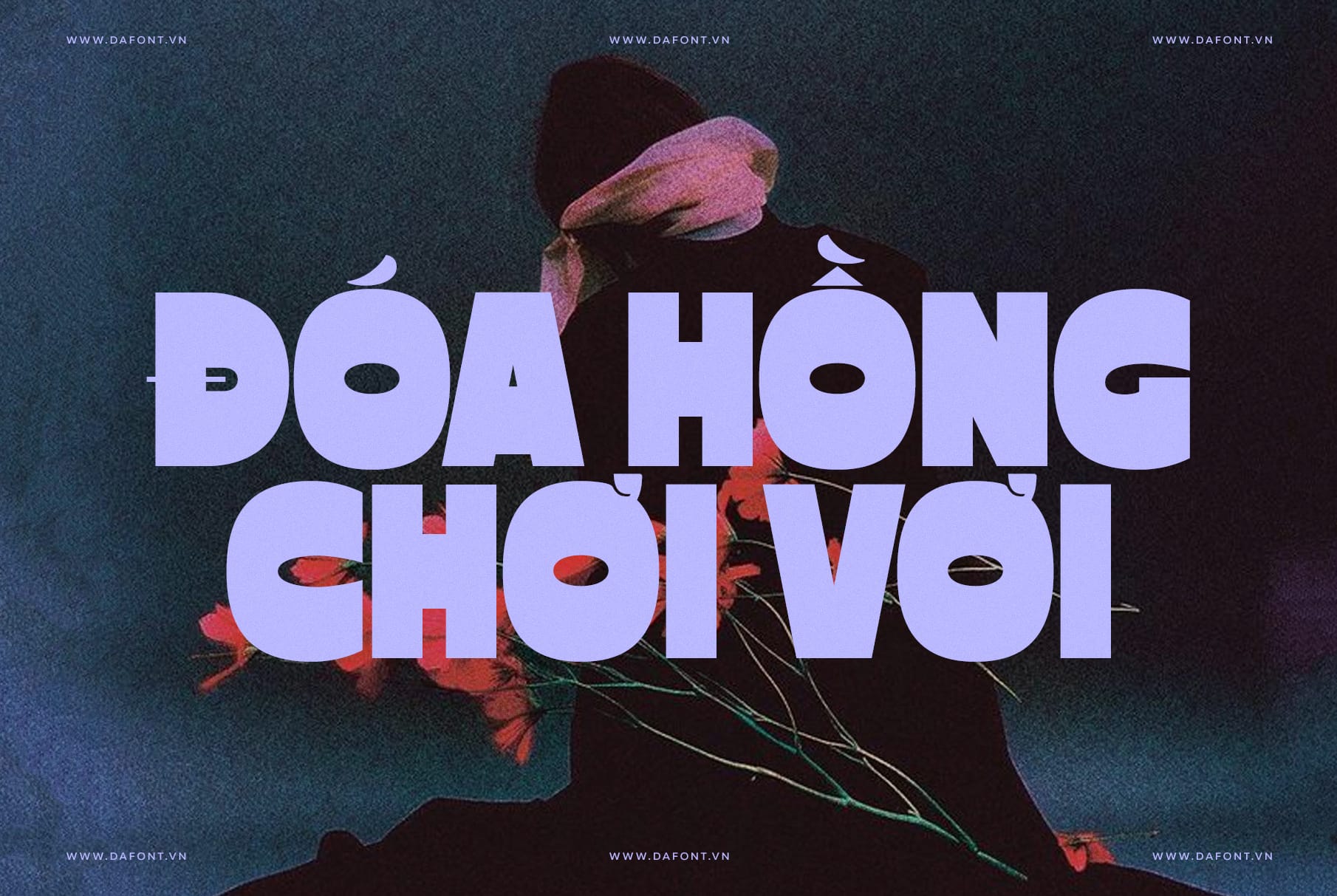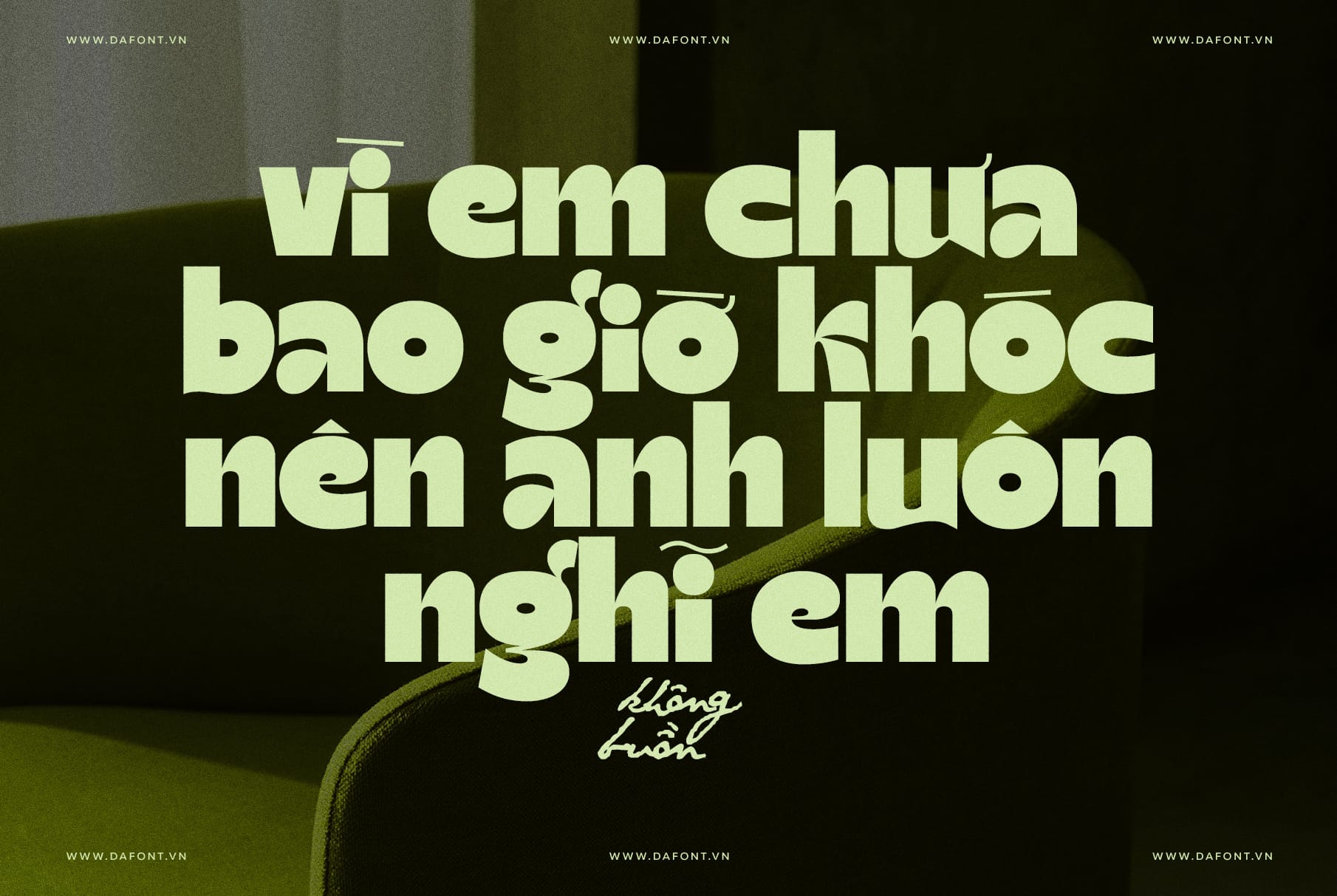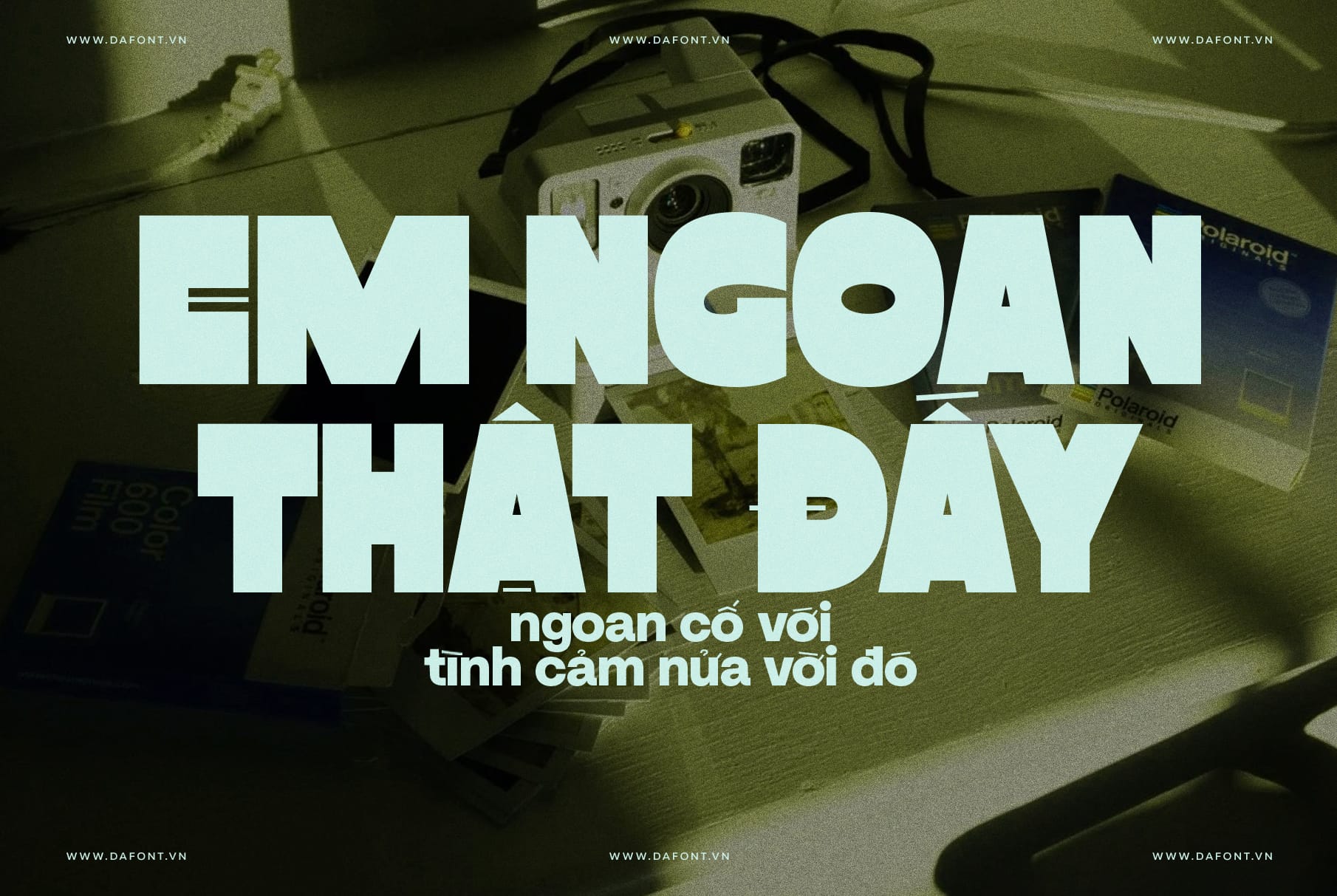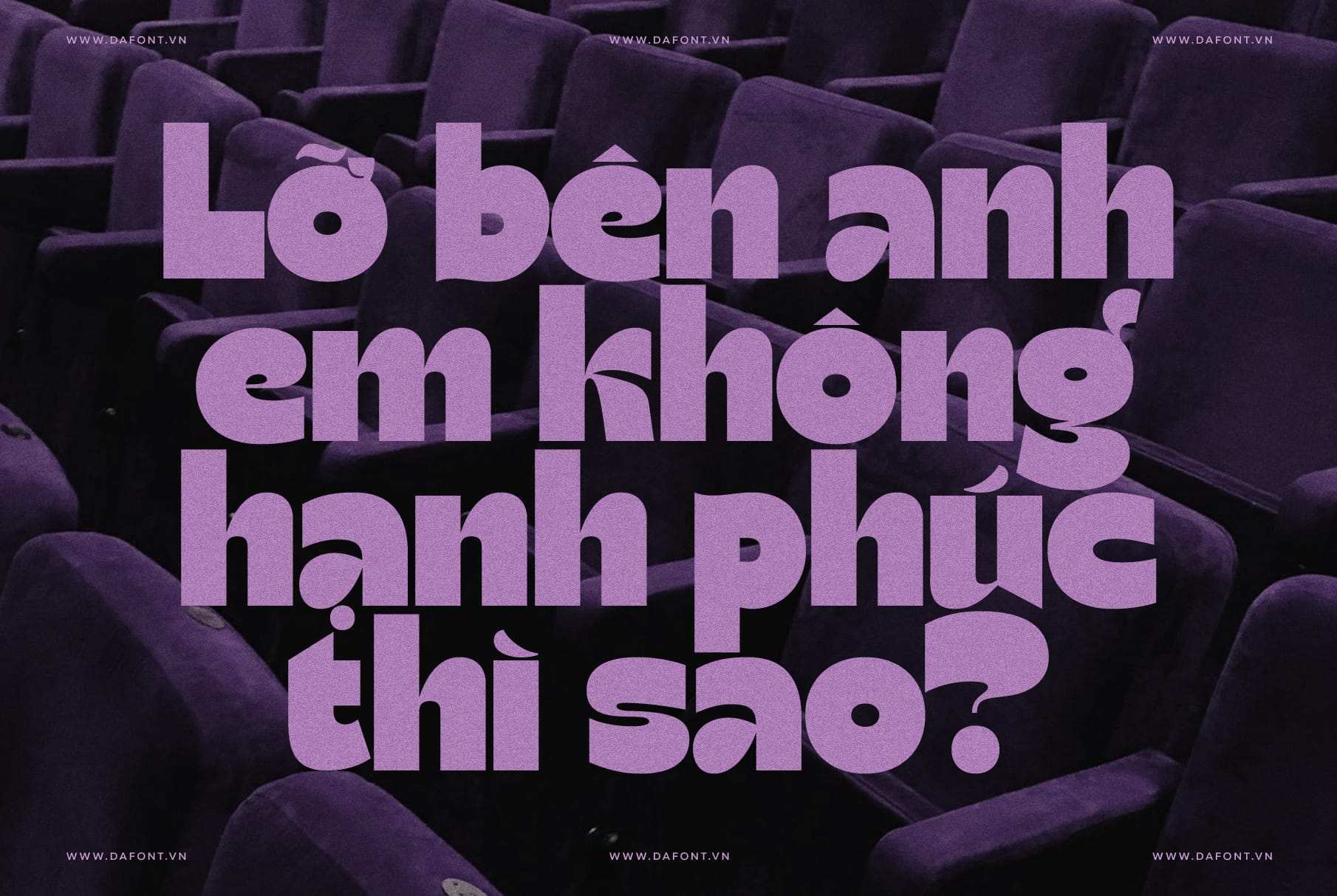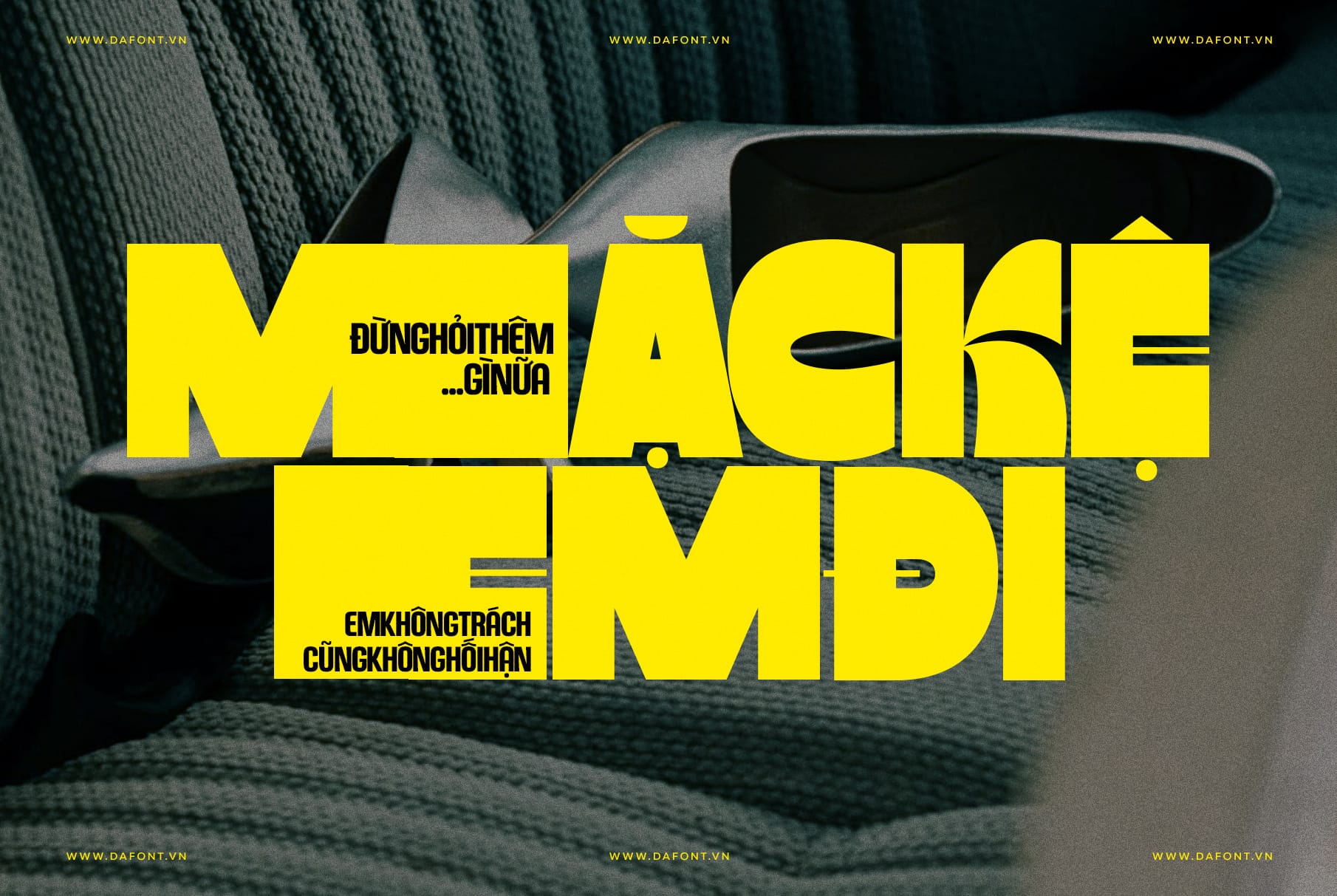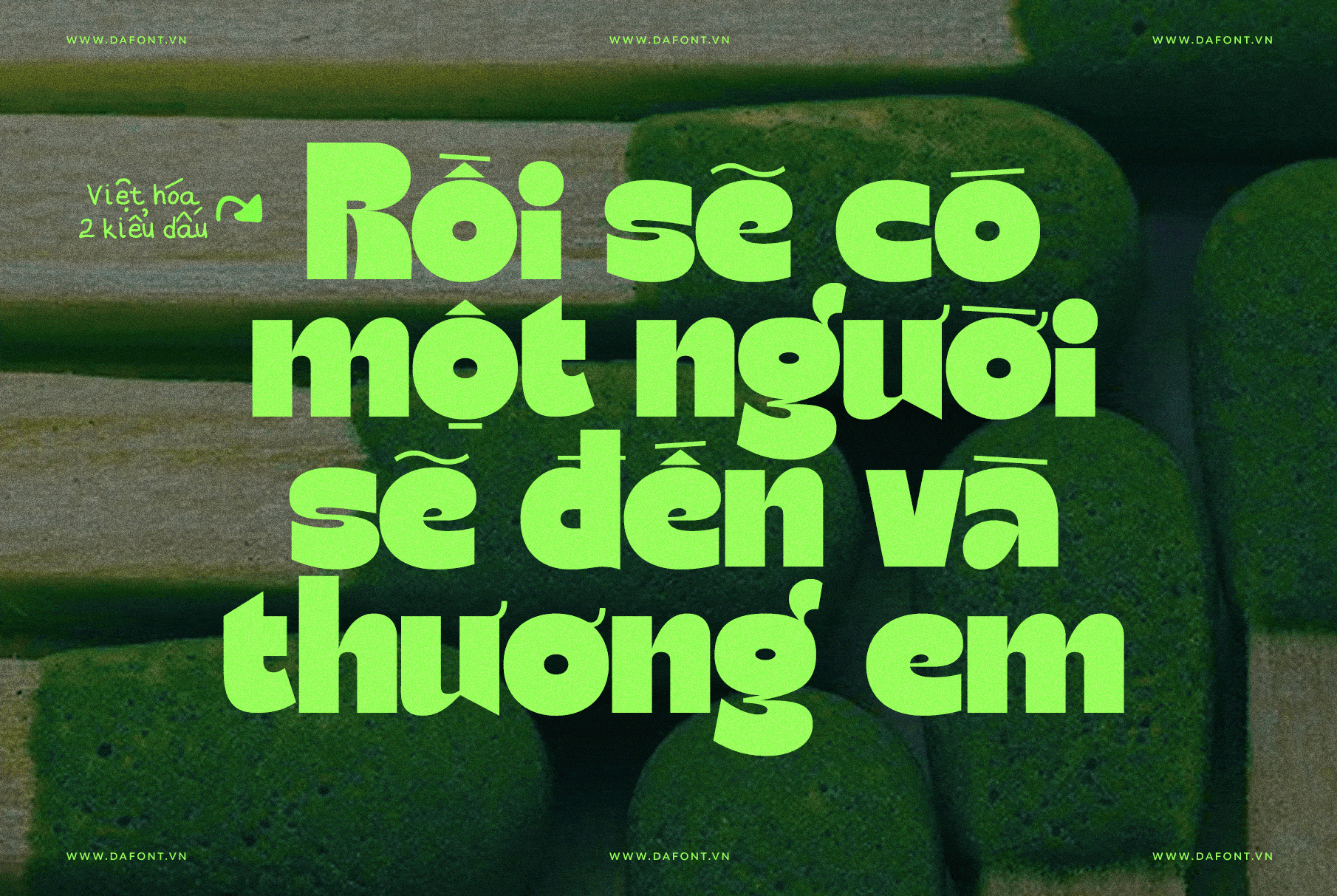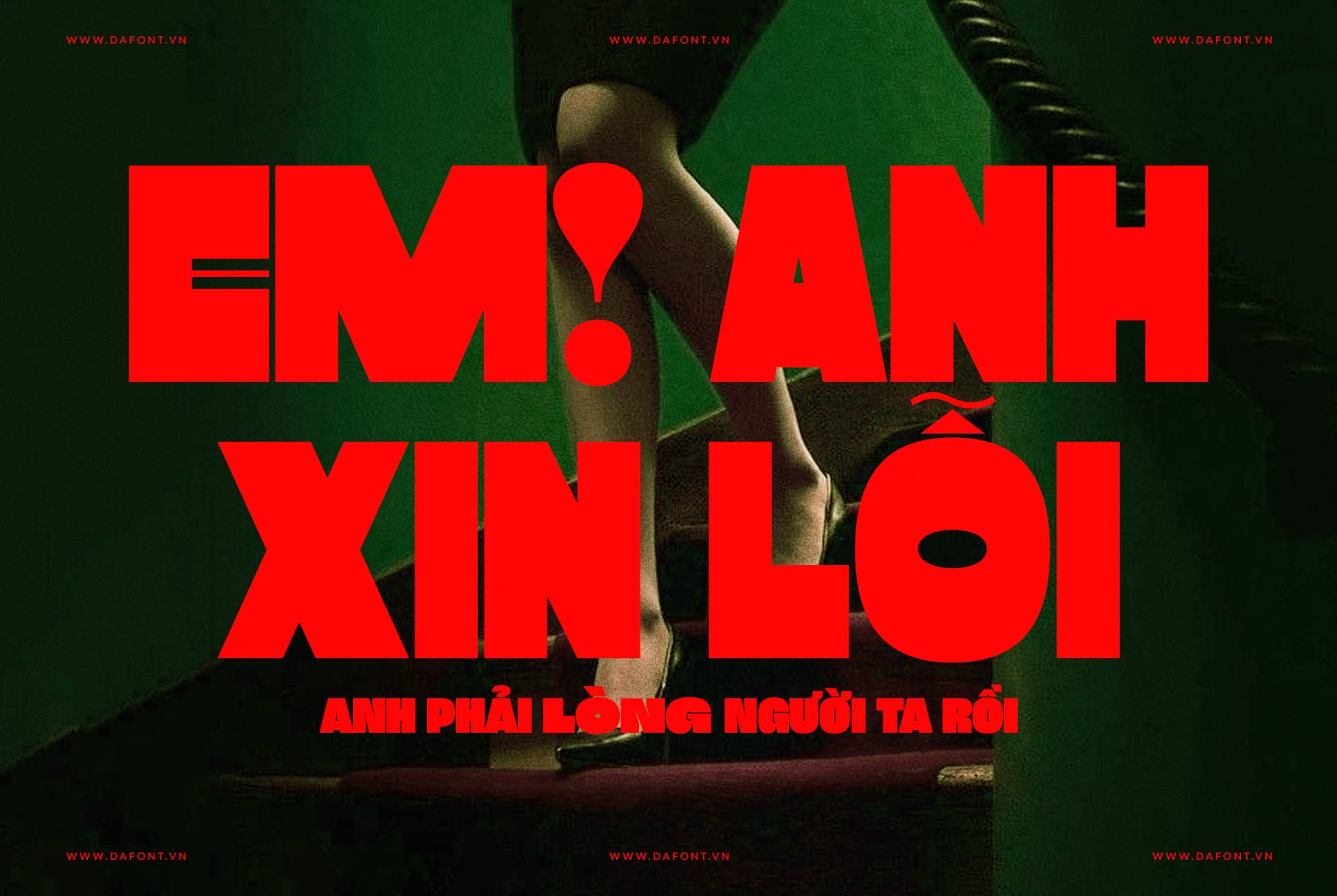
DFVN TAN – FLOWER MARKET là một kiểu chữ display được thiết kế với tinh thần mạnh mẽ, cổ điển nhưng vẫn phóng khoáng và hiện đại. Mỗi ký tự trong font như một bông hoa nở rộ giữa khu chợ đầy sắc màu – vừa có cấu trúc vững chắc, vừa có nhịp điệu tươi vui và giàu cảm xúc.
Với các đường nét dày, các đường cong bo tròn tinh tế và những chi tiết “quirky” đặc trưng, DFVN TAN – FLOWER MARKET thể hiện sự cân bằng hoàn hảo giữa vẻ retro hoài niệm và tinh thần sáng tạo đương đại. Đây là kiểu chữ sinh ra để thu hút ánh nhìn, tạo điểm nhấn mạnh mẽ cho các dự án cần cá tính thị giác – từ logo thương hiệu, poster nghệ thuật, bao bì sản phẩm, cho tới bài đăng mạng xã hội.
Không chỉ dừng lại ở vẻ đẹp hình khối, font còn thể hiện sự tinh tế qua cấu trúc hình học chắc chắn và độ tương phản rõ nét, giúp thiết kế của bạn trở nên nổi bật, tự tin và tràn đầy năng lượng.
Đặc điểm nổi bật DFVN TAN - FLOWER MARKET
Các đặc điểm nổi bật của TAN - FLOWER MARKET tập trung vào khả năng gây ấn tượng mạnh ở cỡ lớn, chất hiện đại–retro vui tươi, và sự linh hoạt trong ứng dụng thương hiệu, in ấn và mạng xã hội.
Nét chữ đậm, mạnh mẽ và chắc chắn
DFVN TAN - FLOWER MARKET mang phong cách display bold với thân chữ to, dày và cân đối. Mỗi ký tự như một khối hình học được gọt giũa kỹ lưỡng, mang lại cảm giác vững chãi, sang trọng và đầy tự tin. Khi dùng ở kích thước lớn, font tạo hiệu ứng thị giác mạnh, giúp tiêu đề hoặc logo nổi bật ngay từ cái nhìn đầu tiên.
Cảm hứng retro pha hiện đại
Lấy cảm hứng từ typography cổ điển của thập niên 70–80, TAN – FLOWER MARKET mang đến không khí hoài niệm nhưng vẫn phảng phất nét đương đại và tinh tế. Các đường cong bo tròn, phần đầu chữ mềm mại cùng tỉ lệ hiện đại giúp font dễ ứng dụng trong nhiều xu hướng thiết kế hiện nay — từ vintage poster, branding, đến editorial art direction.
Việt hóa với 2 kiểu dấu tinh chỉnh riêng biệt
Phiên bản DFVN Việt Hóa được hoàn thiện với hai bộ dấu tiếng Việt khác nhau:
• Kiểu dấu mặc định: Cân đối, rõ nét, phù hợp cho thiết kế thương hiệu, tiêu đề hoặc nội dung cần sự chuyên nghiệp.
• Kiểu dấu mảnh mang phong cách retro: Nhẹ nhàng, nghệ thuật và có độ “chơi chữ”, giúp font trở nên độc đáo và đậm chất cá nhân trong các thiết kế mang phong cách vintage, poster nghệ thuật hoặc typography sáng tạo.
Cả hai kiểu dấu đều được tinh chỉnh cẩn thận về kerning, khoảng cách và vị trí dấu, đảm bảo hiển thị hài hòa ở mọi kích thước và nền màu khác nhau.
Cá tính vui tươi nhưng tinh tế
DFVN TAN - FLOWER MARKET không hề khô cứng như nhiều font geometric. Các nét cong nhẹ và bo góc mềm mại giúp font vừa vui tươi, thân thiện, vừa giữ được sự chuyên nghiệp - rất phù hợp với các thương hiệu hướng đến cảm xúc trẻ trung nhưng vẫn tinh tế.
Tối ưu cho tiêu đề, logo và bao bì
Đây là font display nên phát huy tốt nhất ở heading, banner, poster hoặc wordmark thương hiệu. Với độ dày ổn định và độ nhận diện cao, font thể hiện cực kỳ rõ nét trên cả màn hình và bản in, đặc biệt khi kết hợp cùng tông màu nổi hoặc nền vintage.
Hỗ trợ đa ngôn ngữ - Việt hóa hoàn chỉnh
Ngoài bộ Latin mở rộng, phiên bản Việt hóa của DFVN đảm bảo hiển thị đầy đủ dấu tiếng Việt, bao gồm các ký tự phức tạp như với độ cao dấu và cân chỉnh kerning chuẩn xác.
Đường nét mượt mà, tỷ lệ hài hòa
Dù mang form chữ dày, font vẫn có độ cong mượt và tỷ lệ giữa thân - chân chữ hợp lý, giúp tạo cảm giác tự nhiên, không nặng nề. Khi ghép nhiều chữ, tổng thể vẫn giữ được nhịp điệu thị giác ổn định và đẹp mắt.
Phù hợp nhiều phong cách thiết kế
Dễ dàng kết hợp với các font sans-serif hoặc serif mảnh để tạo độ tương phản. Phong cách của DFVN TAN - FLOWER MARKET phù hợp với nhiều tông mỹ thuật: retro hoài cổ, boho trẻ trung, hoặc tối giản phá cách.
Kết luận
DFVN TAN - FLOWER MARKET là một kiểu font mạnh mẽ dành cho các designer và thương hiệu muốn nổi bật giữa đám đông. Với phong cách bold, retro và hiện đại cùng khả năng ứng dụng linh hoạt, nó có thể tạo nên sức hút ngay từ cái nhìn đầu tiên. Nếu bạn đang tìm kiếm một font đầy cá tính để làm logo, poster, tiêu đề mạng xã hội hoặc bao bì sản phẩm - TAN - FLOWER MARKET chắc chắn là lựa chọn mà bạn nên cân nhắc.